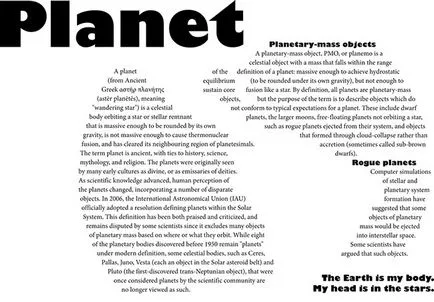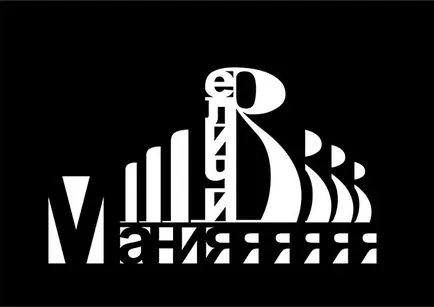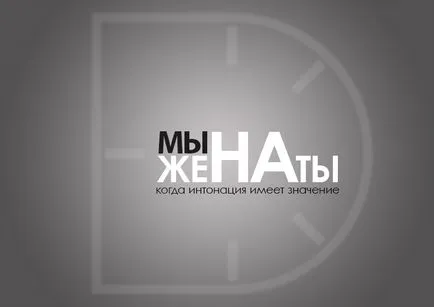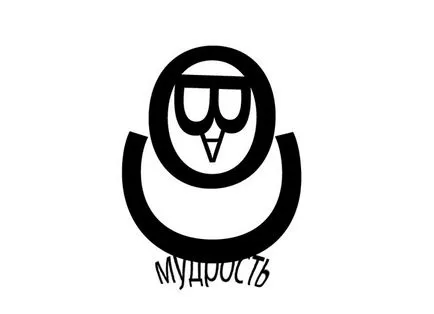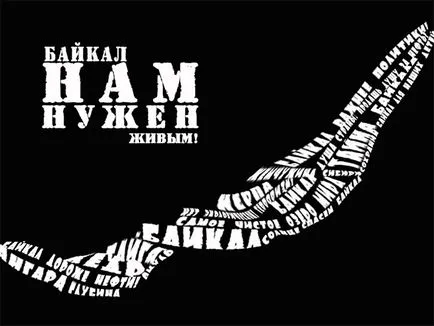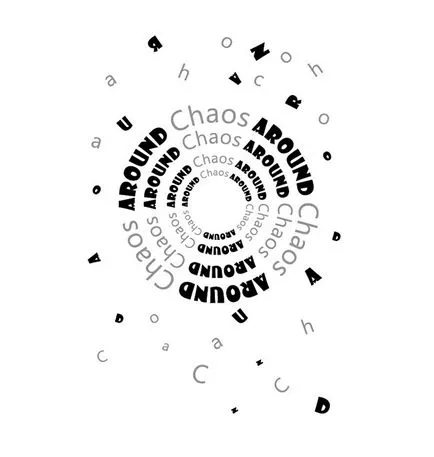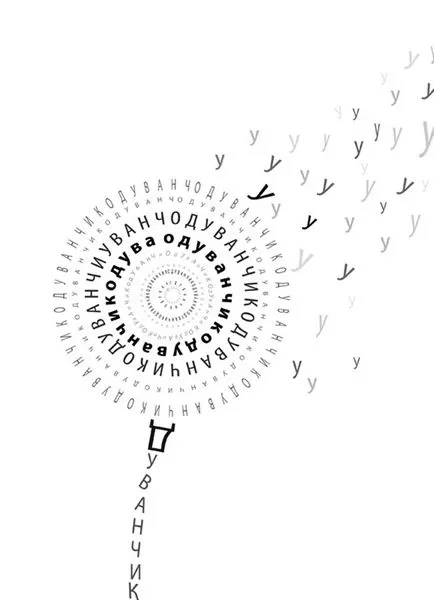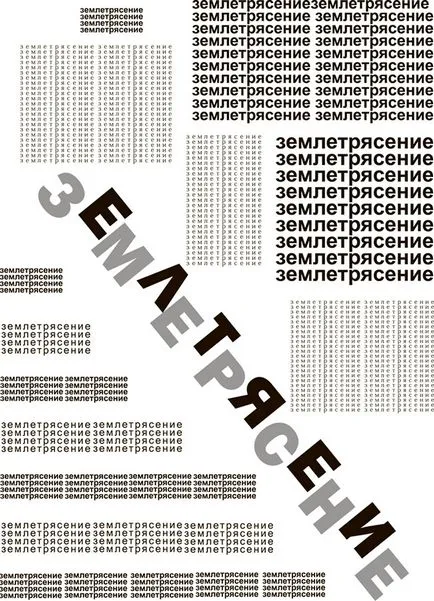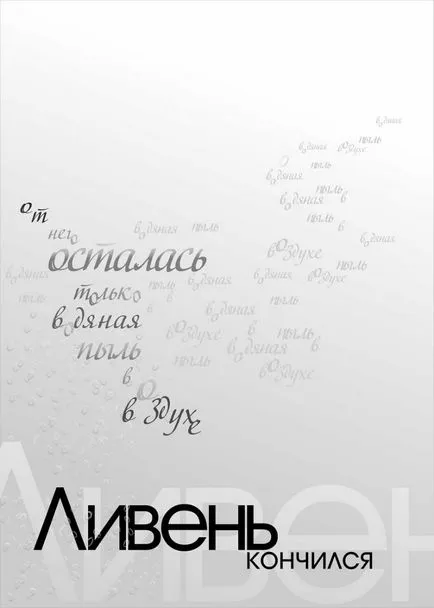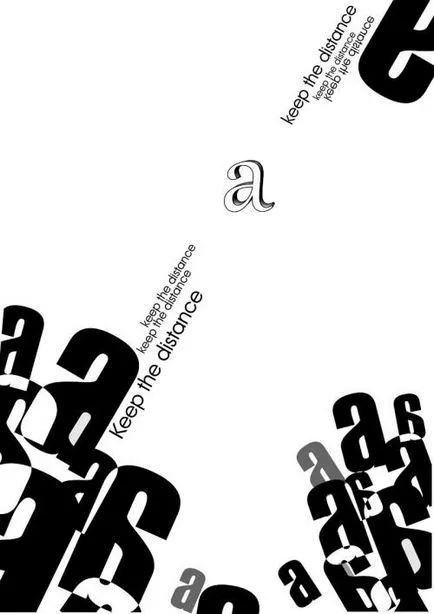
tipografie creativ de formare "
Vă sugerez să uiți la unele dintre lucrările executate la una din clasele de formare. Tema a fost ca să vină cu și executa compoziția arbitrare pe acest subiect, folosind doar elemente de text și font.
Andrey Filimonov
Catherine Sosedova
Tema primul dintre cele două lucrări este vorbitorul.
În plus, efectul părților atașat deformare deliberată a caracterului și o schimbare treptată a culorii de la gri închis la alb strălucitor. Singura compoziție element de neshriftovoy (scuze pentru încălcarea mică sarcinilor) - linie orizontală, care este situat pe treimea inferioară a înălțimii foii vizual și deoarece creează un suport antet mai multe litere pe o suprafață orizontală.
Cea de a doua compoziție este formată din cuvinte versuri Fiecare Road, și, după cum sugerează și numele, este conceput pentru a fi asociat cu drumul. Este, în general, mai static și echilibrată decât cea anterioară, nu numai datorită axei centrale de simetrie, dar, de asemenea, din cauza fundal alb. Mișcarea aici îndreptată vizual spre centrul foii, și apoi - în planul frontal în sus. Acest efect este realizat nu numai prin reducerea dimensiunii punctului și spațierea (imitație perspectivă), dar, de asemenea, din cauza treptată „decolorare“ de litere. Drumul, așa cum au fost „capete“ cu cuvintele «mă face» și aproximativ o treime din înălțimea foii, ci de sus. Această proporție (2/3) - una dintre cele mai armonios percepute de către om.
În ceea ce privește setul cu cască - atunci aici este folosit doar un singur - KabelC Book Regular, deși aici, în unele perechi au avut de a face cu kerning.
Melchakov Yuri
Gulyaev Irina
Compoziția mea păstra distanța - o variație pe tema „cioara alba“ .În centru - litera „o“, care este destul de diferit de cele pe care-l înconjoară. Ele sunt mai mari ca dimensiune, simbolizează capul agresiune. Păstra distanța liniile sunt aranjate astfel încât să indice centrul compoziției. Este un fel de o săgeată sau un pistol, care vizează în direcția străin.
Pentru a doua compoziție lui, am luat linia și subțire. literatură. Starea de spirit generală - liric. Pentru a sublinia acest lucru, am ales scenariul. El, spre deosebire de Antiqua și grotescă mai puțin formale. Mai mult decât atât, aduce un sentiment de relație personală, dushevnosti.Voobsche, fraza începe cu cuvintele SFÂRȘITUL dusului. Nu știu dacă să-l ia în această prezentare este convenabil. Am motivat: ploaie torențială - această putere, elementul, care reprezintă confuzie, teamă și lacrimi în parte altcuiva. Prin urmare, era necesar să se facă aceste cuvinte de tipul relevant. Dar! Pe de altă parte, a fost de peste, iar acest lucru este important! În aer, a existat doar o ceață - este un simbol al renașterii, învierii pentru a începe mai bine! Aceste cuvinte ar trebui să fie ușor de făcut, cu senzație de „aer“ și „lumină“. Despre bukovki - cum ar fi picături de ploaie sau ceață. Nu știu dacă am face spațiu negativ pentru a lucra la crearea unei dinamici sau nu gestionate.
Sutuga Olga
Churzin Alina
tatiana Chzhan
Catherine Yatskova
Subiect: "Megalomania".
Eu folosesc un fundal negru, ca obiectul principal de „B“, pare a fi cea mai avantajoasă și expresiv decât alb. Pentru a sublinia măreția „B“ a folosit o parte a literei B. „Jelic“ Literele scrise în parte a scrisorii B ca într-un recipient, și ultima literă a cuvântului „Măreția“, „I“ - o literă a unui cuvânt cu „mania“ și „măreție“. Cuvântul „Mania“ este scris de utilizarea spațiului negativ. Pentru a continua seria ritmica, precum și pentru o mai mare stabilitate compozițională a repetat „I“, sau mai degrabă spațiul său negativ, alb pe negru.
Delver Elena
Shipov Aleksey